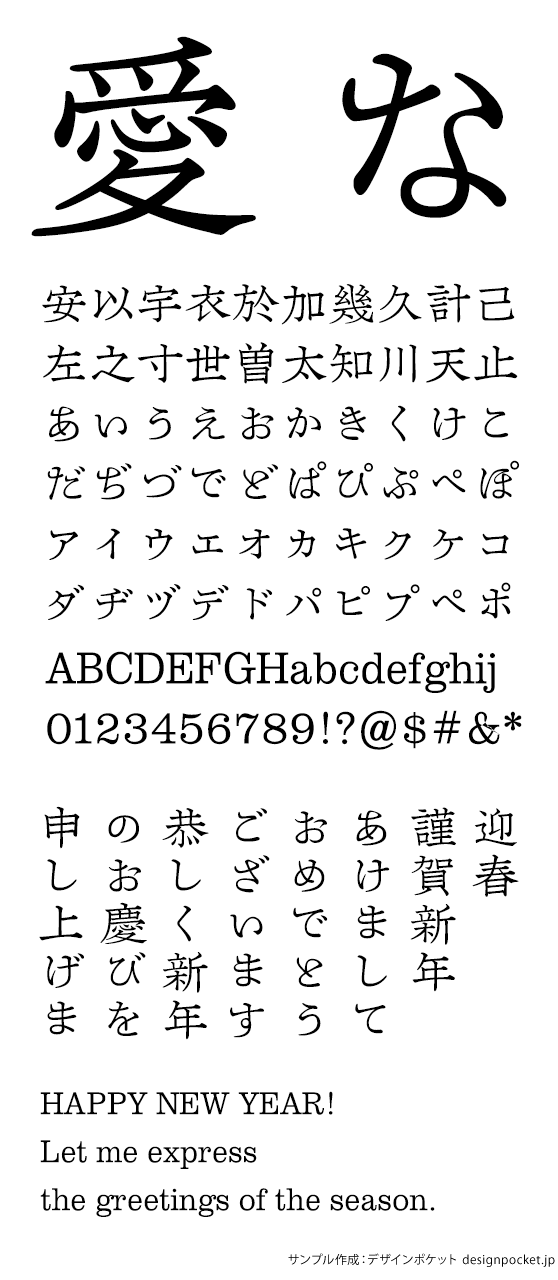
アンチック体
KOみなもと方広M
KOMinamotoHoko-M
『新撰讃美歌』(警醒社、1888)の見出し語から復刻した和字アンチック体「みなもと」に、北宋代の仏教経典『大方廣佛華巖経』(龍興寺、990–994)にもちいられた字様をもとに翻刻した中世安竹体「方広」、ロバート・ベズリによる「クラレンドン」が掲載されている『印刷活字総合見本帳』(ファン・ストリート活字鋳造所、1857年)所収の見本から復刻したスラブセリフ体「K.E.Pisces」を組み合わせたKOみなもと方広BKのファミリーで、メディウム・ウエイトです。